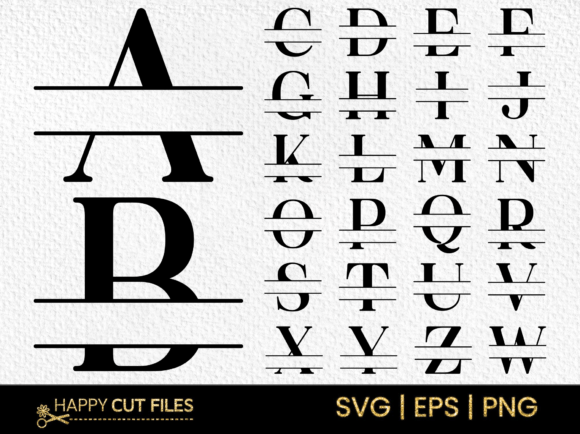
Monogram Svg Modern Split Font Letter
Encontrar os elementos de design certos pode ser um desafio, mas Monogram Svg Modern Split Font Letter oferece uma coleção excepcional que eleva o seu trabalho instantaneamente.
Quer você esteja criando produtos POD (Print on Demand), convites de casamento ou gráficos para mídias sociais, Monogram Svg Modern Split Font Letter é a escolha ideal.